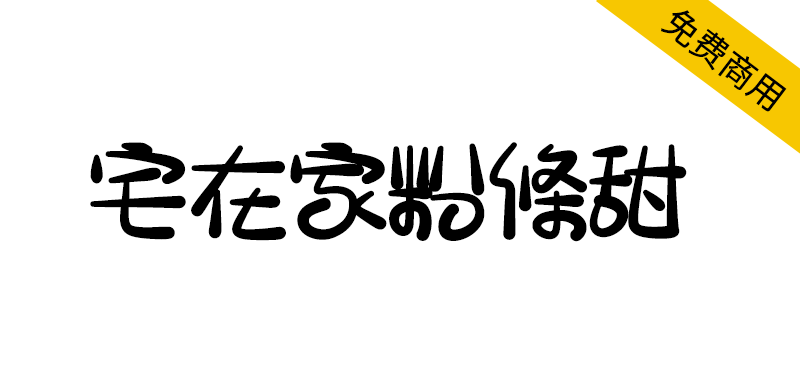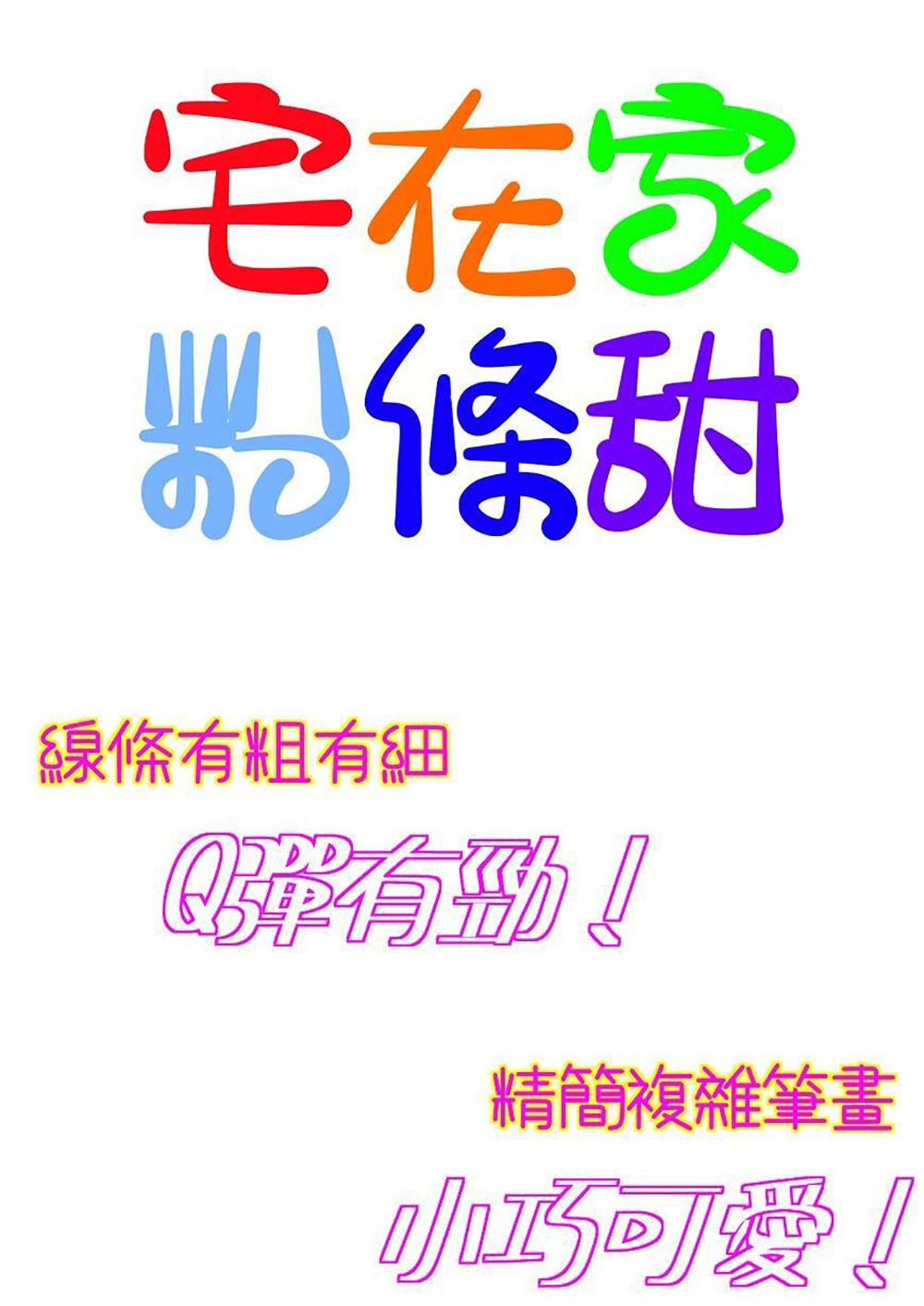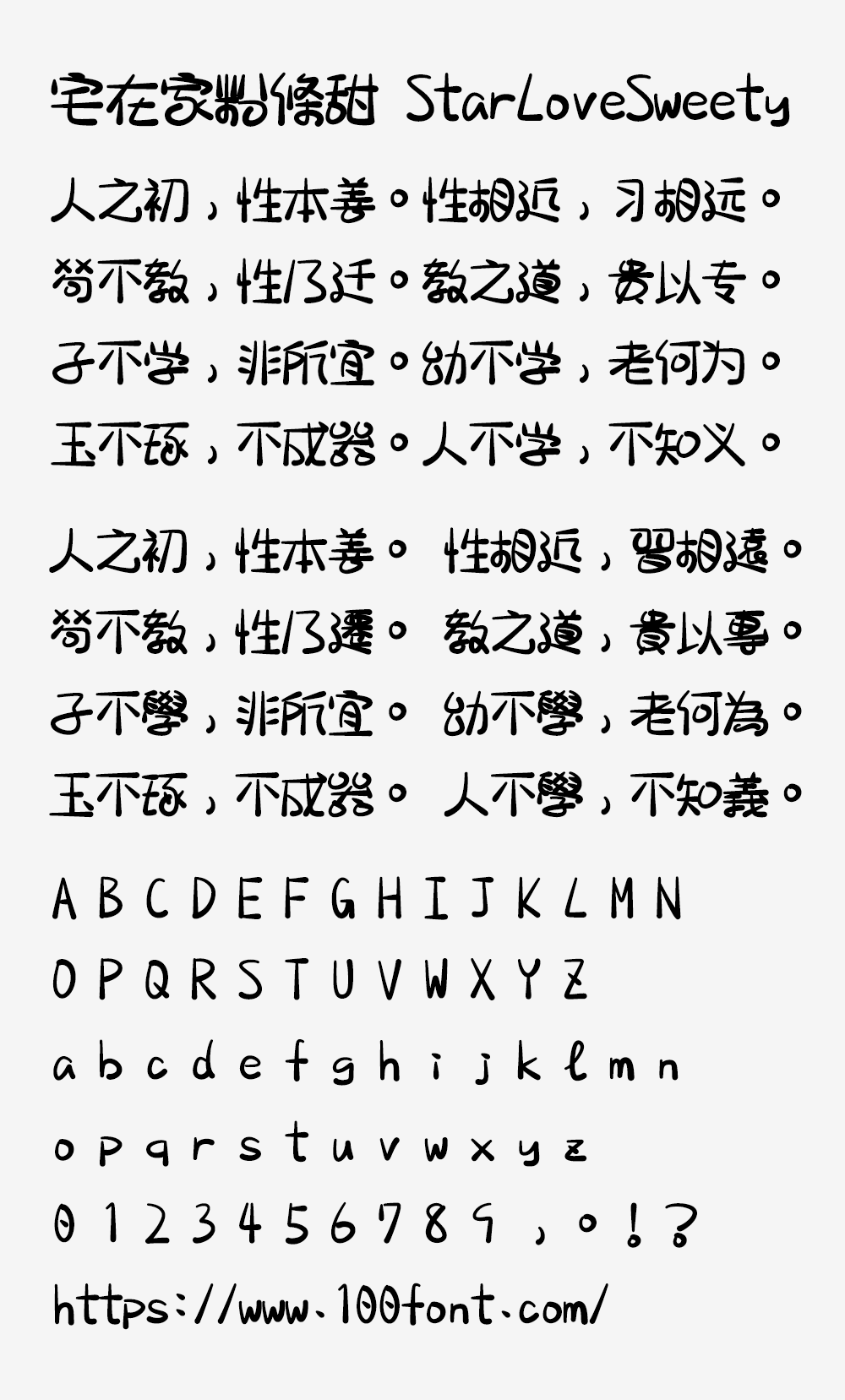
宅在家粉条甜(StarLoveSweety)是台湾省网友"天天宅在家"设计创作的一款免费商用字体,字体风格生动活泼,具有圆润Q弹、小巧可爱的艺术特色,其线条粗细变化自然,视觉效果突出,非常适合应用于文化宣传设计、商业品牌广告、产品包装设计等多种场景。镶嵌改作商标都随便使用,不用特别再告知。
宅在家粉条甜完整实现了简体标准6763个汉字的制作,因此不必担心简体字的显示问题,该字体对简体中文、繁体中文都提供了良好的支持。